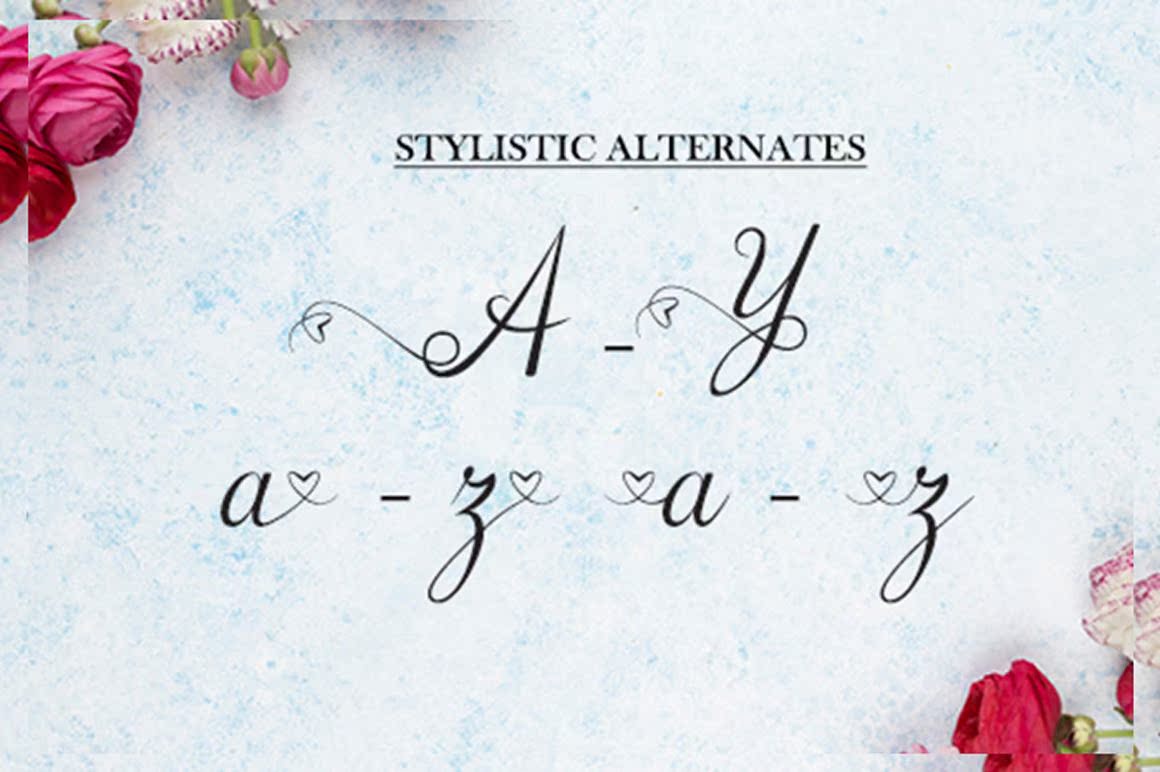
KylieAnaturand StyleshishScriptFont。该字体在插图、徽标和品牌、摄影、广告、水印、社交媒体符号等方面都非常完美。该字体是经过编码的,意味着您可以访问这些符号和Swashease!KylieAnaturand StyleshishScriptFont。该字体在插图、徽标和品牌、摄影、广告、水印、社交媒体符号等方面都非常完美。该字体是经过编码的,意味着您可以访问这些符号和Swashease!